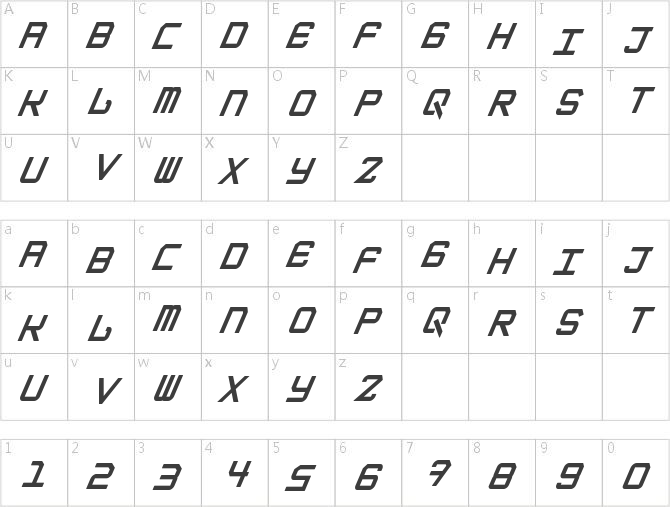
EpicenterBlackItalic 詳情頁
EpicenterBlackItalic字體字庫是一款讓人賞心悅目、百看不厭的英文字體,適合各類廣告和產(chǎn)品包裝設(shè)計應(yīng)用,字體大小0.03MB,格式為ttf字體,上傳用戶是82年的拉菲,作者/版權(quán)方為未知